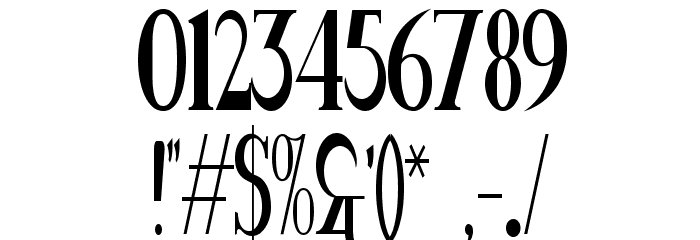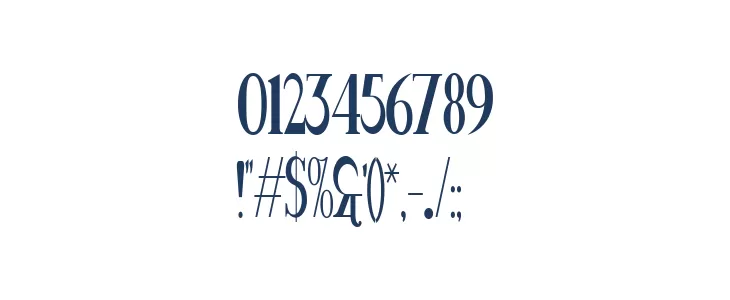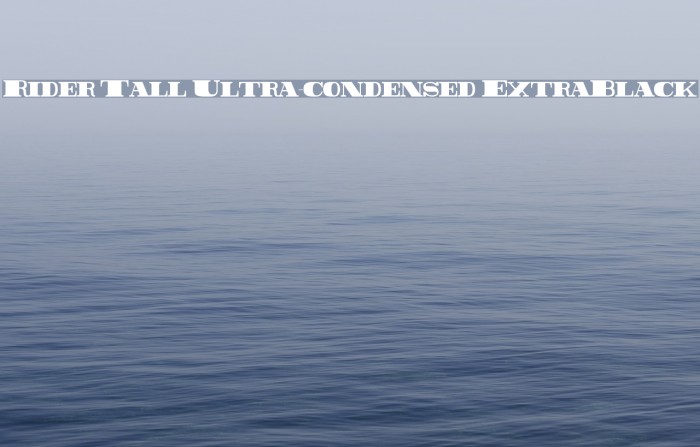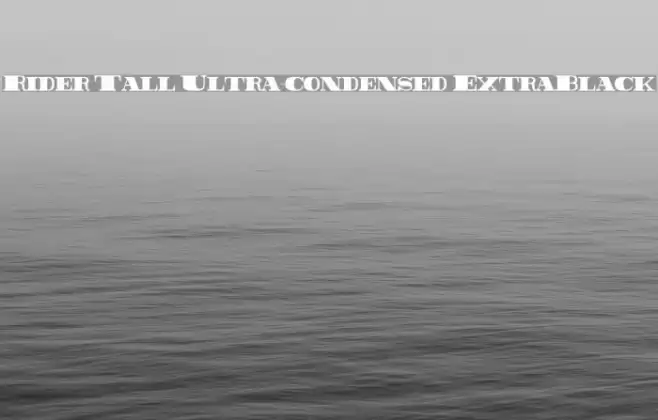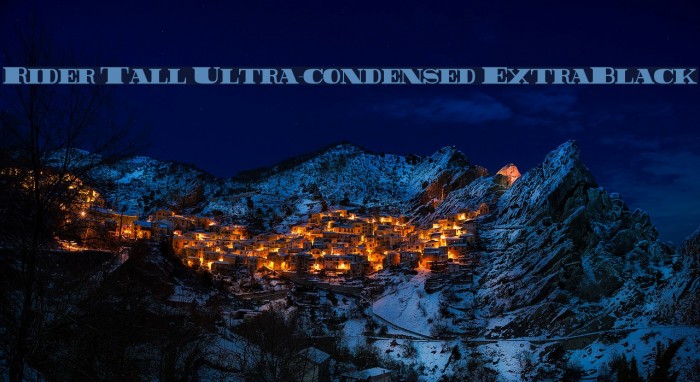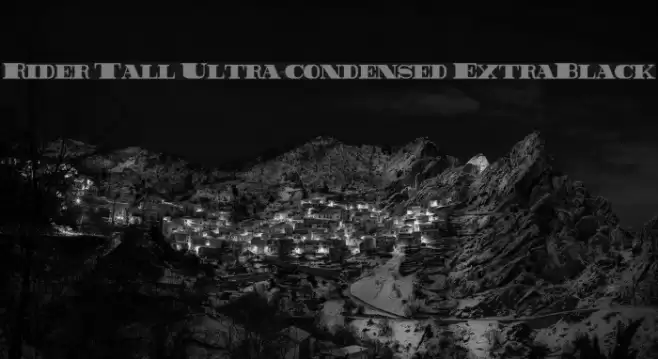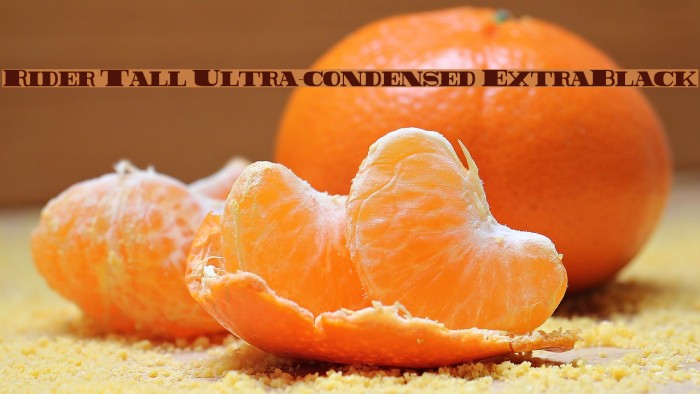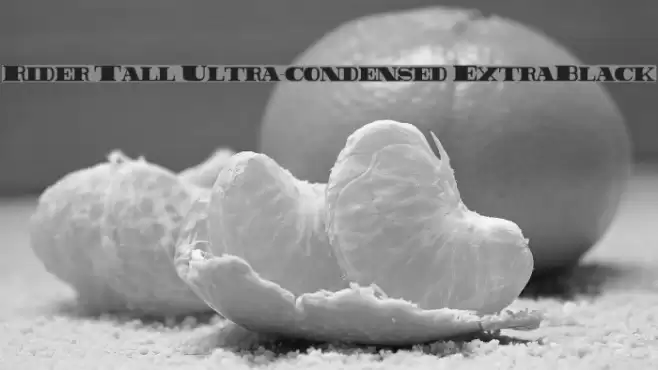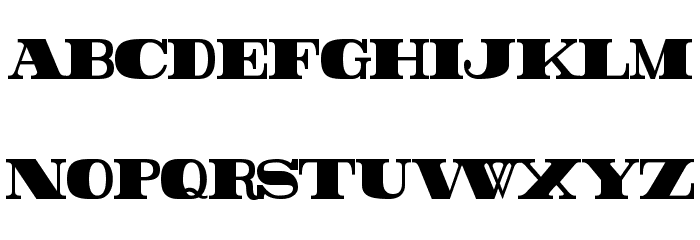
Rider Tall Ultra-condensed ExtraBlack Font
Fonts by Mans Greback - www.mawns.com
| 推荐项目 | Ideal for headlines, posters, and branding projects that require a bold and authoritative presence. |